2023 年 15 种最佳德语字体(免费和付费)
已发表: 2023-09-10您是一名平面设计师,正在寻找完美的字体来增强您的项目吗? 别再犹豫了! 在这篇博文中,我们将探索 15 种最好的德语字体,它们一定会提升您的设计并吸引您的受众。
但您可能想知道,为什么专门使用德语字体? 好吧,让我来回答你。 德国字体具有独特的魅力和性格,可以为任何设计带来优雅、精确和真实的感觉。 那么,让我们深入探索德国字体的世界!
在本文中,我们将分享一份精选的 15 种德文字体列表,这些字体在全球设计师中广受欢迎。 我们将为您提供每种字体的简要概述,包括其独特的特征、风格元素和推荐的使用场景。
无论您是从事品牌项目、编辑设计,还是为社交媒体创建引人注目的视觉内容,这些字体都将为您的设计带来独特的德国风格。
那么,让我们开始吧! 在以下部分中,我们将展示令人惊叹的德语字体,它们非常适合为您的项目增添一丝精致和专业精神。
每种字体都有其独特的风格,因此您将有很多选项可供选择,具体取决于您想要实现的语气和情绪。 准备好发现市场上最好的德语字体,并将您的设计提升到一个新的水平!
最佳优质德语字体
为在项目中寻求优雅和精致的完美触感的图形设计师推出最佳优质德语字体。
沉浸在这些字体所提供的精湛工艺和对细节的关注中,并发现它们如何将您的设计提升到新的高度。 不要错过探索本文中介绍的各种字体 - 它们一定会激发您的灵感并让您着迷。
德语
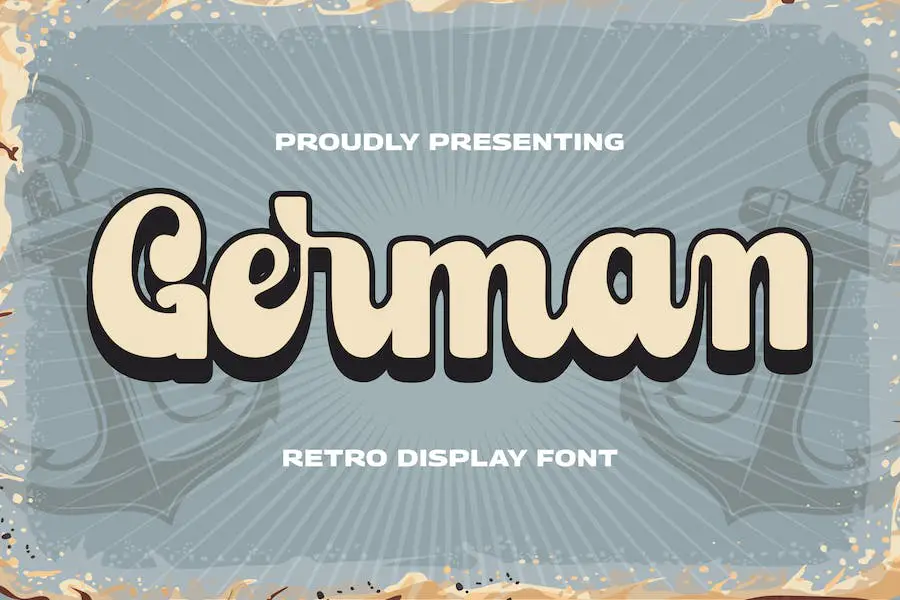
German 是 Runsell 创建的一款多功能字体产品,非常适合各种项目。 无论您是从事摄影、徽标、品牌推广还是特殊活动,这款字体都能满足您的需求。
使用 German,您可以轻松增强项目的设计并使其脱颖而出。 该字体提供独特而时尚的外观,将吸引您的受众。 它的多功能性使您可以在各种设置和环境中使用它,这使其成为任何图形设计师的宝贵资产。
德国的魅力在于它能够将您的设计提升到一个新的水平。 其干净、现代、引人注目的美感为您的工作增添了一抹专业和精致。
您可以依靠这种字体给您的客户留下持久的印象,并使您的设计在竞争中脱颖而出。
自私
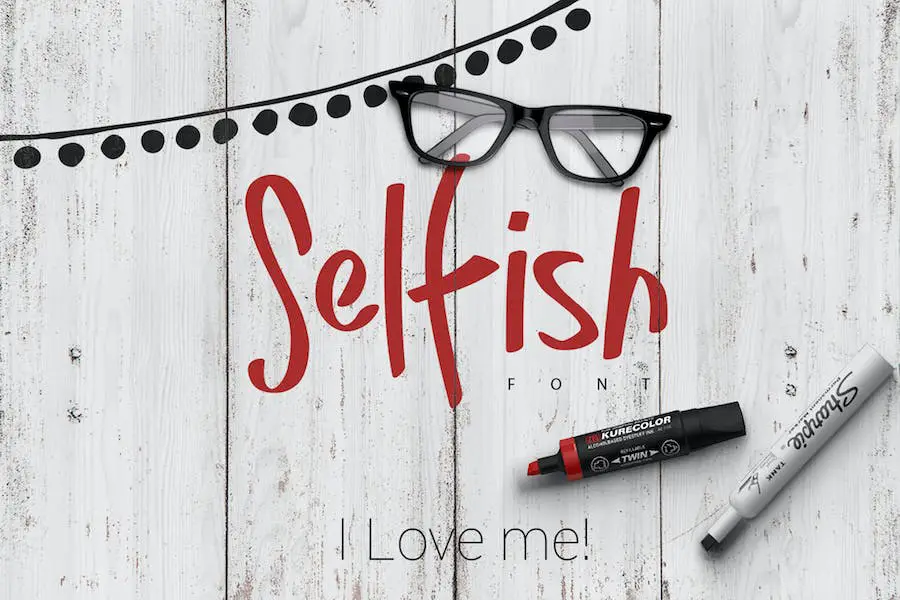
Selfish 是一种脚本和手写字体,可为您的设计项目增添一丝优雅和个性化。 凭借其独特的艺术品质,这种字体非常适合希望增强作品视觉吸引力的图形设计师。
它的属性包括模仿手写自然动作的美丽流畅的字体风格。 笔触细腻优雅,给你的设计带来精致感。 这些角色具有手工制作的感觉,为您的作品增添个性化的触感。
这种字体还具有多功能性,允许您在各种设计应用程序中使用它。 无论您是创建徽标、婚礼请柬还是社交媒体图形,Selish 都可以将您的项目提升到新的高度。
其有机且真实的外观使其适合数字和印刷设计。
昆西·塞里夫
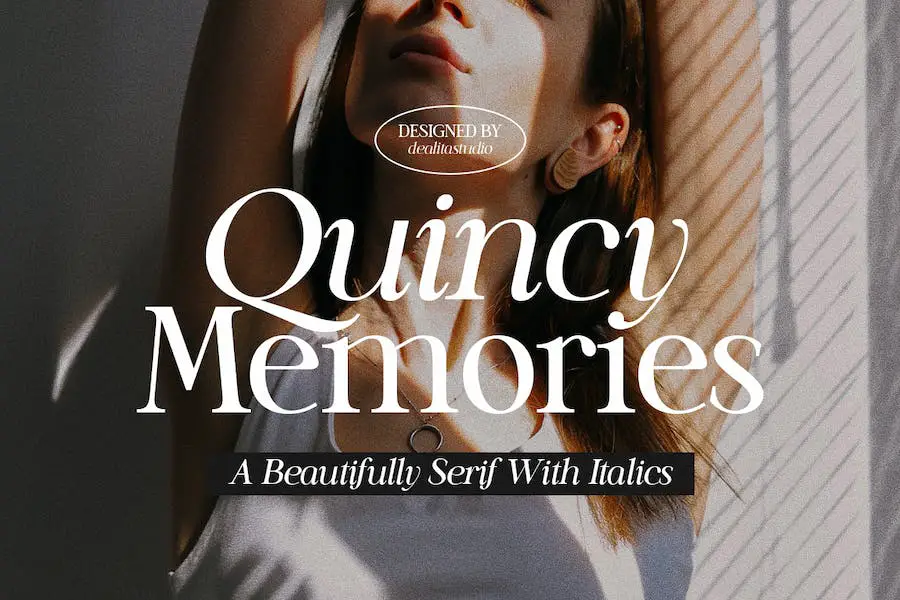
Quincy Serif 是一种令人惊叹的衬线字体,带有斜体的额外好处。 这种字体非常适合为任何项目增添一丝优雅和精致,特别是那些需要正式外观的项目。
Quincy Serif 凭借其时尚精致的设计,是一种多功能字体,可在各种不同的材料上使用。 无论您是在处理邀请函、名片,甚至是正式文件,Quincy Serif 都一定会给您留下深刻的印象。
有吸引力的斜体选项为您的文本增添了一丝风格和风格,使您能够以微妙的倾斜来强调某些单词或短语。 这是为您的设计增添深度和个性而不压倒整体美感的完美方式。
Quincy Serif 精美复杂的字体一定会吸引眼球并吸引人们对您的内容的关注。 其简洁的线条和精确的细节打造出抛光且专业的表面效果,一定会给客户留下深刻的印象并提升项目的视觉吸引力。
谜
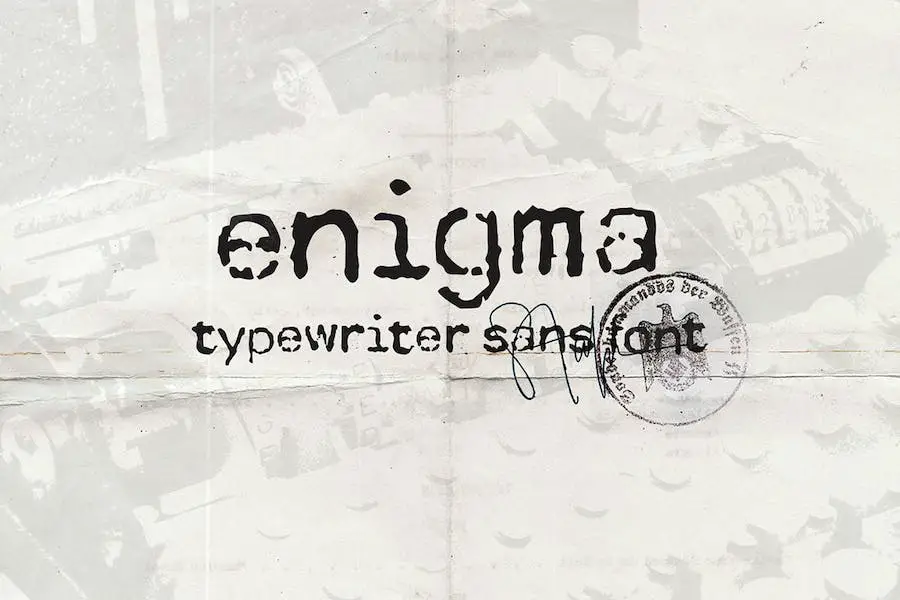
Enigma 是一种名为“It Typewriter”的字体,可让您通过重新创建旧文档和纸张的外观和感觉来为您的设计带来一丝怀旧之情。 它的灵感来自过去的德国机器,为您的项目带来真正的复古氛围。
无论您是在制作复古海报、历史书籍封面还是主题网站,这种字体都会让您的观众回到过去。
Enigma 以其独特而鲜明的风格捕捉了老式打字机的精髓。 每个角色都经过精心设计,模仿旧打字文本的缺陷和怪癖,为您的设计增添真实感。
略微不均匀的字体和不规则的间距营造出质朴和手工制作的感觉,非常适合捕捉昔日的魅力。
Enigma 的突出特点之一是它对细节的关注。 该字体的设计者竭尽全力确保每个字符都忠实于原始打字机风格。
从经典的打字机按键形状到字母的磨损边缘,这种字体真正提供了真实的复古体验。
罗吉
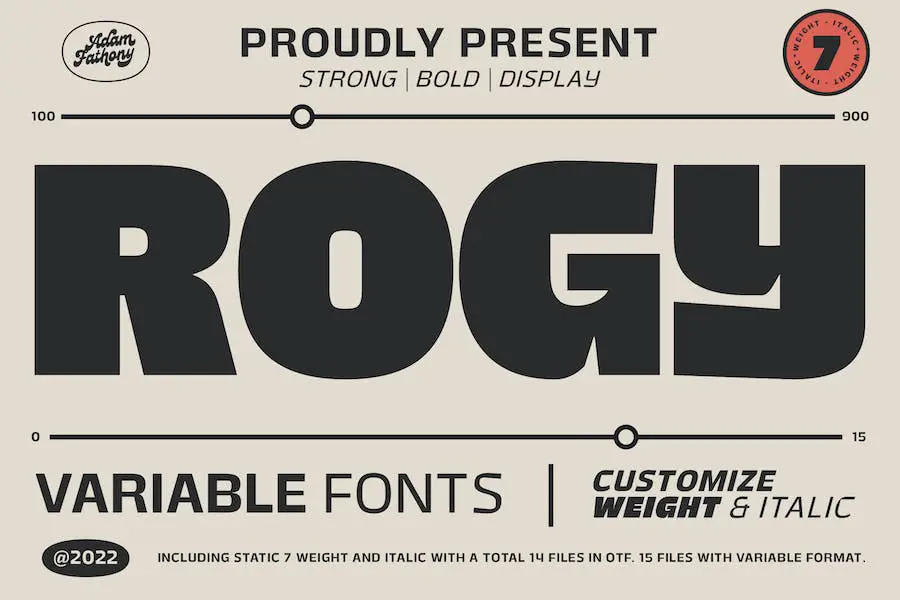
Rogy 是一种现代可变字体,具有刚性和方形外观,但仍然保持高度易读。 凭借其各种宽度选项和斜体样式,它为设计师提供了很大的灵活性来探索、组合和创建独特的设计。
该字体的方形外观为任何项目增添了现代和干净的美感,而其刚性确保每个字符保持一致和结构化的外观。 这使其成为需要时尚专业设计的项目的绝佳选择。
Rogy 的突出特点之一是其可变宽度选项。 这意味着设计者可以调整字符的粗细以满足他们的特定需求。 无论您想要大胆而有影响力的设计,还是更精致、精致的外观,Rogy 都能满足您的需求。
此外,Rogy 还提供一系列斜体样式,可用于强调或创建动态视觉效果。 斜体补充了字体的整体设计,增添了一丝优雅和精致。
纵火案
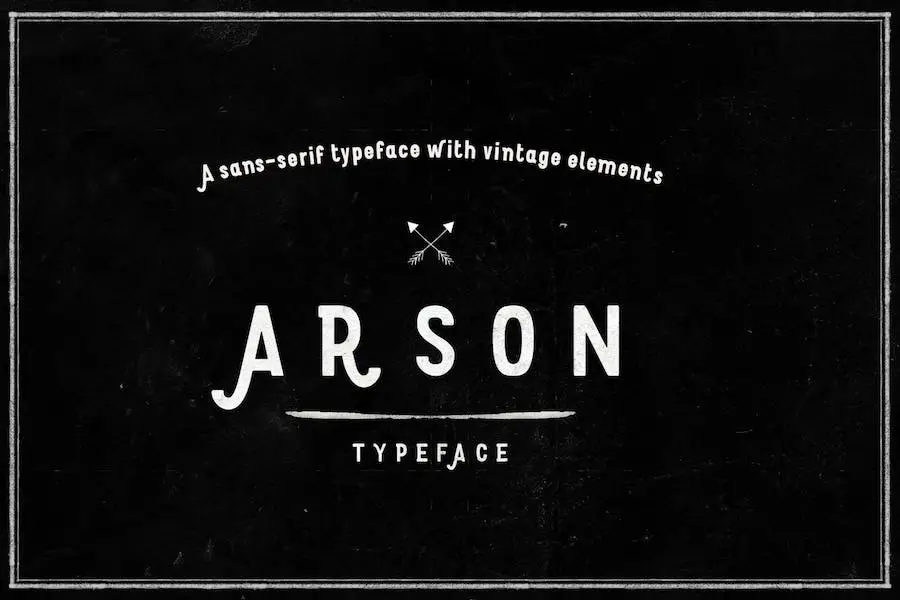
一种多功能、多语言的无衬线字体,带有复古风格。 非常适合复古徽标、品牌、艺术和海报。
Arson 是一种适应性很强的字体,它将现代、圆润的美感与微妙的复古元素结合在一起。 凭借其干净而规则的无衬线设计,它提供了永恒的吸引力,肯定会增强任何图形设计项目。
Arson 的突出特点之一是它的多功能性。 该字体无缝地融合了现代感和一丝怀旧气息,使其成为那些想要创造复古风格设计的人的绝佳选择。
无论您是在制作徽标、品牌材料、艺术品还是海报,Arson 都能为您的项目增添一抹个性和魅力。
但真正让 Arson 与众不同的是它的多语言功能。 该字体支持多种语言,让您可以轻松地向全球受众传达您的信息。
它确保您的设计不受语言障碍的限制,使其成为国际客户或项目的宝贵资产。
德蒙特
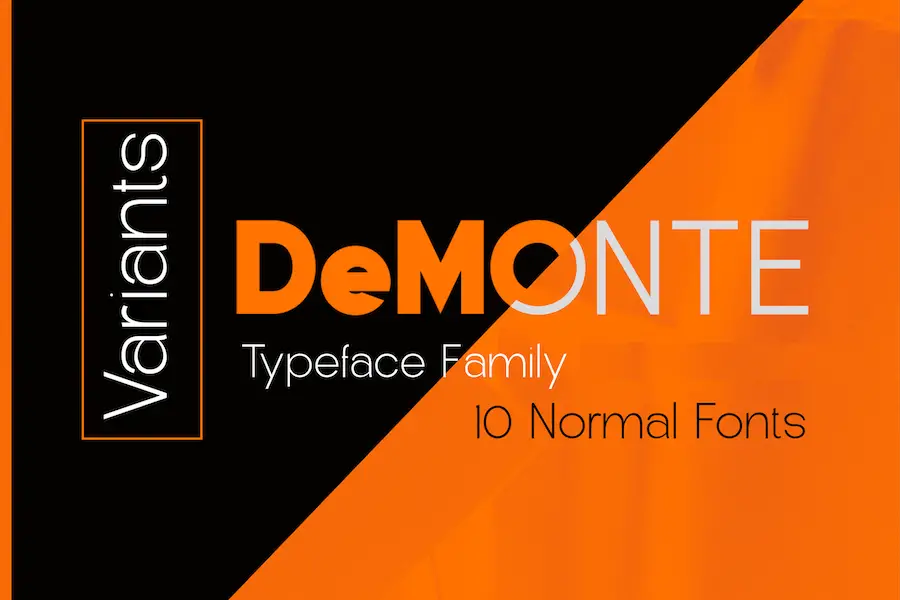
DeMonte 是一种具有现代风格的现代无衬线字体。 该字体系列提供柔和优雅的触感,非常适合针对千禧一代的项目。
凭借其时尚和时尚的设计,DeMonte 一定会增强任何平面设计师的项目并将其提升到一个新的水平。
DeMonte 的突出特点之一是它的多功能性。 它有 10 种不同的重量,让设计师可以根据自己的特定需求选择完美的厚度。
无论您是要创建大胆而引人注目的标题,还是微妙而低调的正文,DeMonte 都能满足您的需求。
该字体系列的另一个重要方面是它的多语言支持。 它被设计为与多种语言兼容,使其成为面向国际受众的项目的绝佳选择。
无论您的目标受众来自哪里,DeMonte 都可以帮助您有效地传达信息。
笨拙
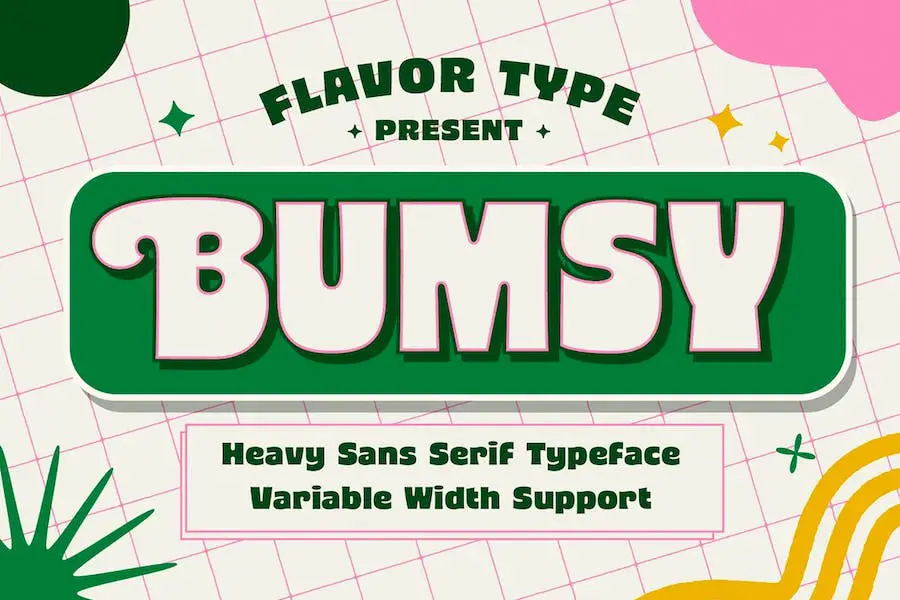
BUMSY 是一款出色的新字体,经过精心设计,完美无缺。 这种重型无衬线字体不仅用途广泛,而且还具有有趣、可爱和美丽的感觉,可以立即吸引您的注意力。 有了 BUMSY,您的设计项目一定会产生持久的影响。
BUMSY 的突出特点之一是它的多功能性。 无论您正在进行什么类型的项目,无论是徽标、海报还是网站,这种字体都可以轻松适应您的需求。
其简洁的线条和大胆的外观使其成为您想要的任何设计风格或概念的绝佳选择。
BUMSY 的另一个优点是它有趣和可爱的感觉。 这种字体为您的设计增添了一丝俏皮感,使它们更具吸引力和引人注目。
无论您是为儿童品牌设计还是只是想为您的作品注入一些个性,BUMSY 都是完美的选择。
滑动
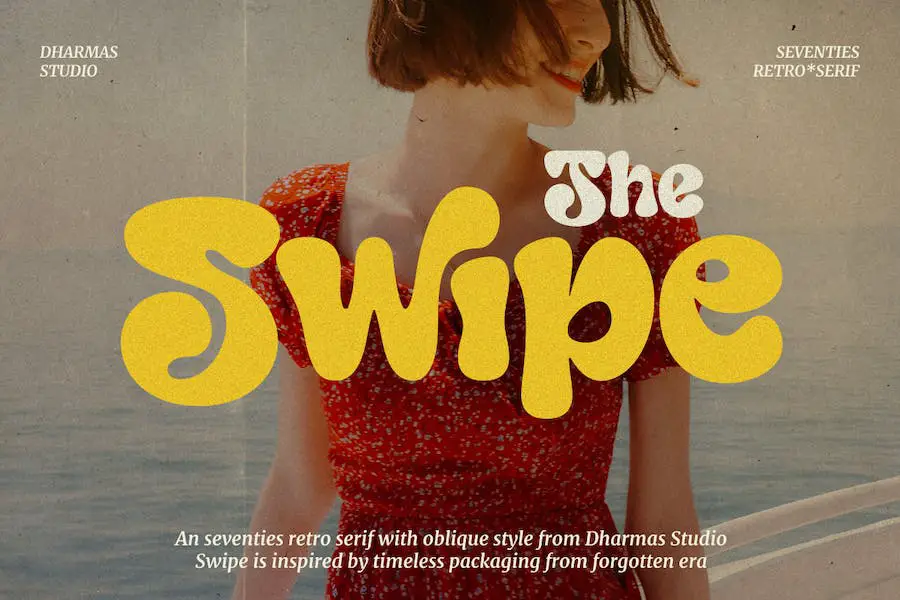
Swipe 是一种七十年代的字体,可为任何设计项目带来复古和有趣的氛围。 凭借其平滑的曲线和柔和的大胆,这种字体创造了令人惊叹的视觉吸引力,将带您回到怀旧时代。
无论您想增添一丝复古魅力还是捕捉七十年代的精髓,Swipe 都是完美的选择。 其规则和倾斜样式提供了多功能性和灵活性,可增强您的设计并将其提升到一个新的水平。
准备好为您的项目注入怀旧感,并通过 Swipe 让它们真正令人难忘。
老艾玛
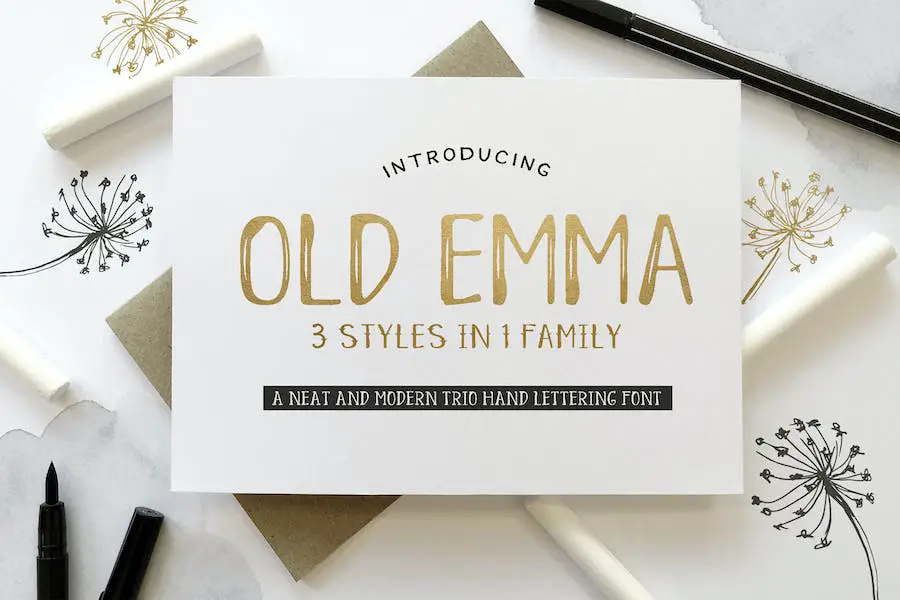
隆重推出 Old Emma,这是一种三重字体,它将现代手写字体风格与无衬线和衬线字体元素相结合。 该字体具有三种不同的风格可供选择 - It、It Decorative 和 It Serif - 为创意混合和匹配提供了无限的机会。
老艾玛为任何设计项目带来了优雅与现代魅力的独特融合。 其现代手写字体风格增添了个人风格,而无衬线和衬线元素则赋予其永恒的品质。
无论您是在制作徽标、海报还是网站,这种字体都会提升您的设计并使其脱颖而出。
Old Emma 的“It”风格干净简约,非常适合时尚现代的设计。 另一方面,它是装饰性的,添加装饰元素,为您的项目带来一丝奇思妙想和俏皮感。
最后,It Serif 风格为您的设计带来经典而精致的感觉,使其成为正式邀请函或品牌材料的理想选择。
最佳免费德语字体
希望为您的设计增添一丝德国风格? 别再犹豫了! 在本节中,我们收集了最好的免费德语字体,它们将使您的项目更上一层楼。 因此,继续检查它们并发现完美的字体来提升您的设计!
FE字体
FE-Font 是一种多功能无衬线字体,专为车牌设计。 它采用等宽字母和数字,旨在通过使其难以篡改并提高机器的可读性来增强安全性。
FE-Font 的独特设计具有稍微不成比例的字符,确保其无法轻易修改或更改。 此属性为车牌增加了额外的安全层,使未经授权的个人更难操纵或伪造它们。
此外,FE-Font 的等宽格式有助于增强机器可读性。 字符之间的均匀间距提高了自动化系统解释车牌信息的准确性和速度,确保可靠和高效的识别。
日耳曼尼亚
Dieter Steffmann 的 Germania 是一种多功能字体,可以极大地增强图形项目的设计。 这种字体展示了德国印刷术的美丽和精确,使其成为平面设计师的流行选择。
Germania 凭借简洁优雅的线条,为任何设计增添一抹精致。
Germania 的突出特点之一是它的多功能性。 它可用于广泛的设计项目,从徽标到海报、网站到邀请函。
其经典而永恒的设计使其适合现代和传统美学,使其能够无缝适应任何创意愿景。
日耳曼尼亚对细节的关注是引人注目的。 每个字母都经过精心制作,确保您的设计具有平衡与和谐的感觉。
该字体还提供了广泛的风格替代和连字,允许您自定义和个性化您的版式以满足您的特定需求。
日耳曼尼卡
Germanica 是由著名设计师 Paul Lloyd 精心打造的字体。 它独特地融合了德国优雅和现代设计,使其成为希望提升项目视觉吸引力的平面设计师的完美选择。
凭借简洁的线条和永恒的美感,Germanica 为任何设计带来精致感。 它的多功能性使其可用于广泛的项目,从标志设计到品牌材料,甚至网站排版。
Germanica 的突出特点之一是对细节的关注。 每条曲线和笔画都经过专业设计,以确保视觉和谐和易读性。 这种精湛的工艺水平体现在每个字符中,从而打造出既美观又实用的字体。
德语字体可用于广泛的设计项目,包括网站、徽标、海报、邀请函等。 但是,重要的是要考虑您想要在设计中传达的整体风格和基调。
虽然德语字体可以带来精致和优雅的感觉,但它们可能并不总是最适合每个项目。 尝试并找到适合您的特定设计目标和目标受众的字体始终是一个好主意。
结论
回顾一下,在本文中,我们探讨了图形设计师可以用来增强其项目设计的 15 种最佳德语字体。 我们讨论了每种字体的独特特征和风格,并提供了示例和建议。